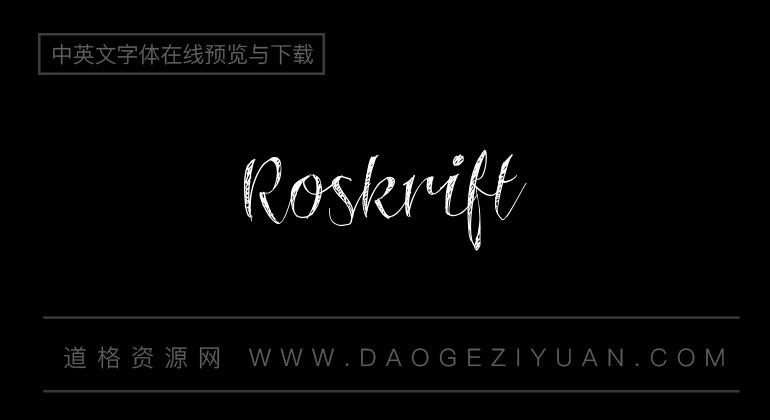
Roskrift
Roskrift是一种手写风格的字体,由瑞典的设计师Johanna Berglund创造。这种字体带有浓重的笔画,类似于毛笔或钢笔书写的效果,但同时具有现代化的感觉。它有趣而独特的外观,适合用于海报、标志、卡片、书籍封面和其他设计项目中。Roskrift字体包括大写字母、小写字母、数字和标点符号,可以在许多设计软件中使用,非常适合需要强调手写感的设计风格。
Roskrift是一款非常不错的手写艺术字体,具有很好的视觉感,适合于文化类的宣传设计、商业类品牌的广告和产品包装设计以及个性化文字排版等较多场景。